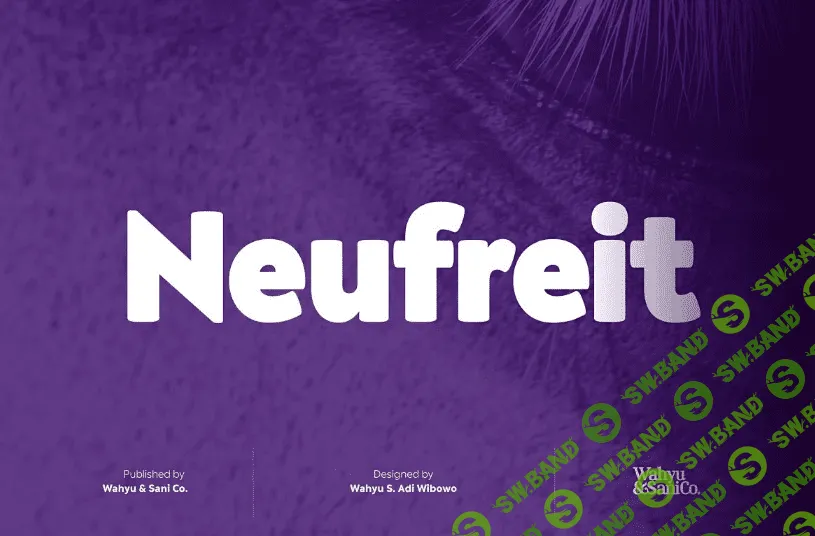
Название: Neufreit Font
Представляем Нойфрайта, младшего брата Крео, но более мягкого и тонкого пропорций с более острыми вершинами и вершинами. Он поставляется в 9 весах с соответствующими курсивными стилями, начиная от ExtraLight и заканчивая Heavy, как самый тяжелый вес.
Это семейство оснащено полезными функциями OpenType, такими как Ordinals, Superiors, Stylistic Sets, Tabular Figures, Standard Ligatures, Fraction, Numerators & Denominators. Каждый шрифт имеет 500+ глифов, которые охватывают Западную и Восточную Европу, и другие языки, основанные на латинице - поддерживается более 200 языков!
Нойфрайт подойдёт для многих творческих проектов. Этот отличительный шрифт идеально подойдёт для логотипов, упаковки, поздравительных открыток, презентаций, заголовков, надписей, плакатов, брендинга, цитат, заголовков, журналов, заголовков, веб-макетов, мобильных приложений, художественных цитат, рекламы, приглашений, дизайна упаковки, книг, заголовков книг и многого другого.
Название: Neufreit Font
Представляем Нойфрайта, младшего брата Крео, но более мягкого и тонкого пропорций с более острыми вершинами и вершинами. Он поставляется в 9 весах с соответствующими курсивными стилями, начиная от ExtraLight и заканчивая Heavy, как самый тяжелый вес.
Это семейство оснащено полезными функциями OpenType, такими как Ordinals, Superiors, Stylistic Sets, Tabular Figures, Standard Ligatures, Fraction, Numerators & Denominators. Каждый шрифт имеет 500+ глифов, которые охватывают Западную и Восточную Европу, и другие языки, основанные на латинице - поддерживается более 200 языков!
Нойфрайт подойдёт для многих творческих проектов. Этот отличительный шрифт идеально подойдёт для логотипов, упаковки, поздравительных открыток, презентаций, заголовков, надписей, плакатов, брендинга, цитат, заголовков, журналов, заголовков, веб-макетов, мобильных приложений, художественных цитат, рекламы, приглашений, дизайна упаковки, книг, заголовков книг и многого другого.